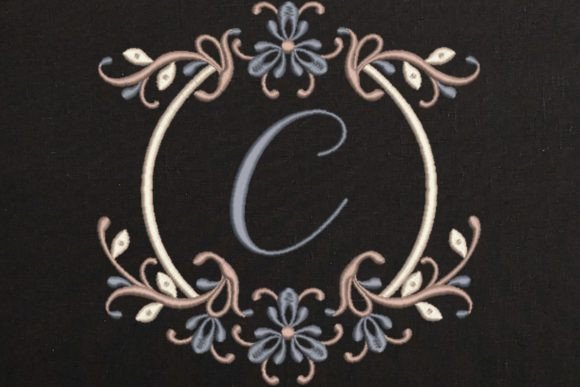
Single Monogram in Frame Letter C
การค้นหาองค์ประกอบการออกแบบที่เหมาะสมอาจเป็นเรื่องท้าทาย แต่ Single Monogram in Frame Letter C นำเสนอคอลเลกชันที่โดดเด่นซึ่งช่วยยกระดับงานของคุณได้ทันที